もちろん商用利用可能で、定番の「Garamond」から、女性向けのデザインに使えそうな「Beauty Style Font Duo」、手書き風の「Portabella」、Tシャツなどのデザインに良さそうな「Starlit Drive Signature Font」など、かなり使えそうな英語フォントが入っています。
Garamond
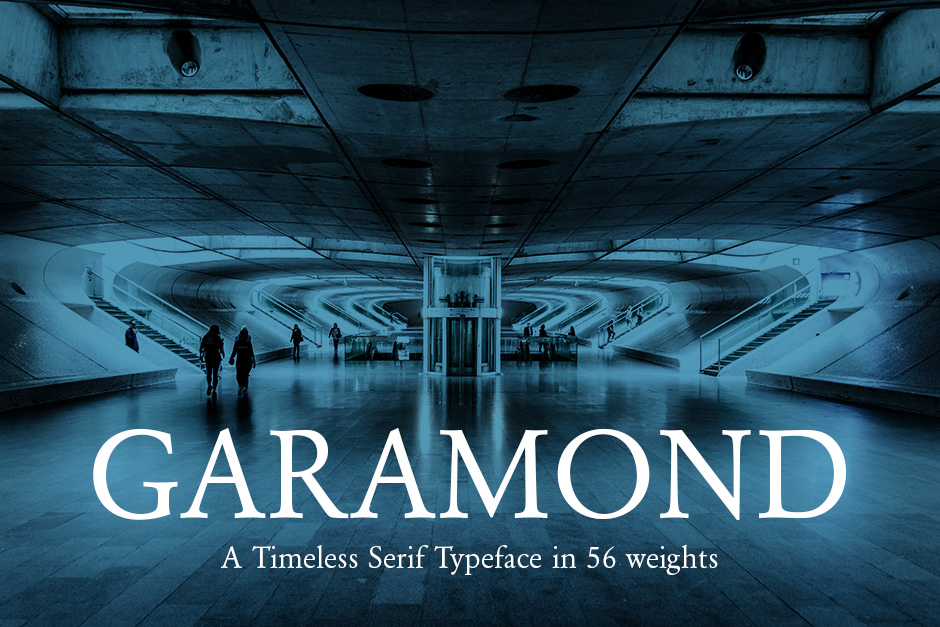
Helveticaと双璧をなすフォント「GARAMOND」
Beauty Style Font Duo
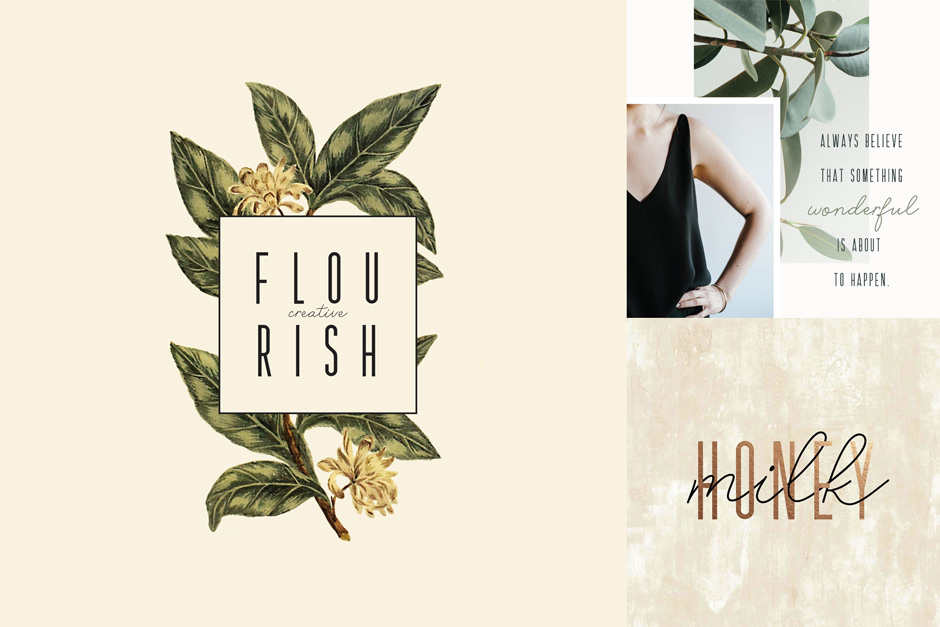
女性向けのデザインに合いそうな「Beauty Style Font Duo」
Portabella
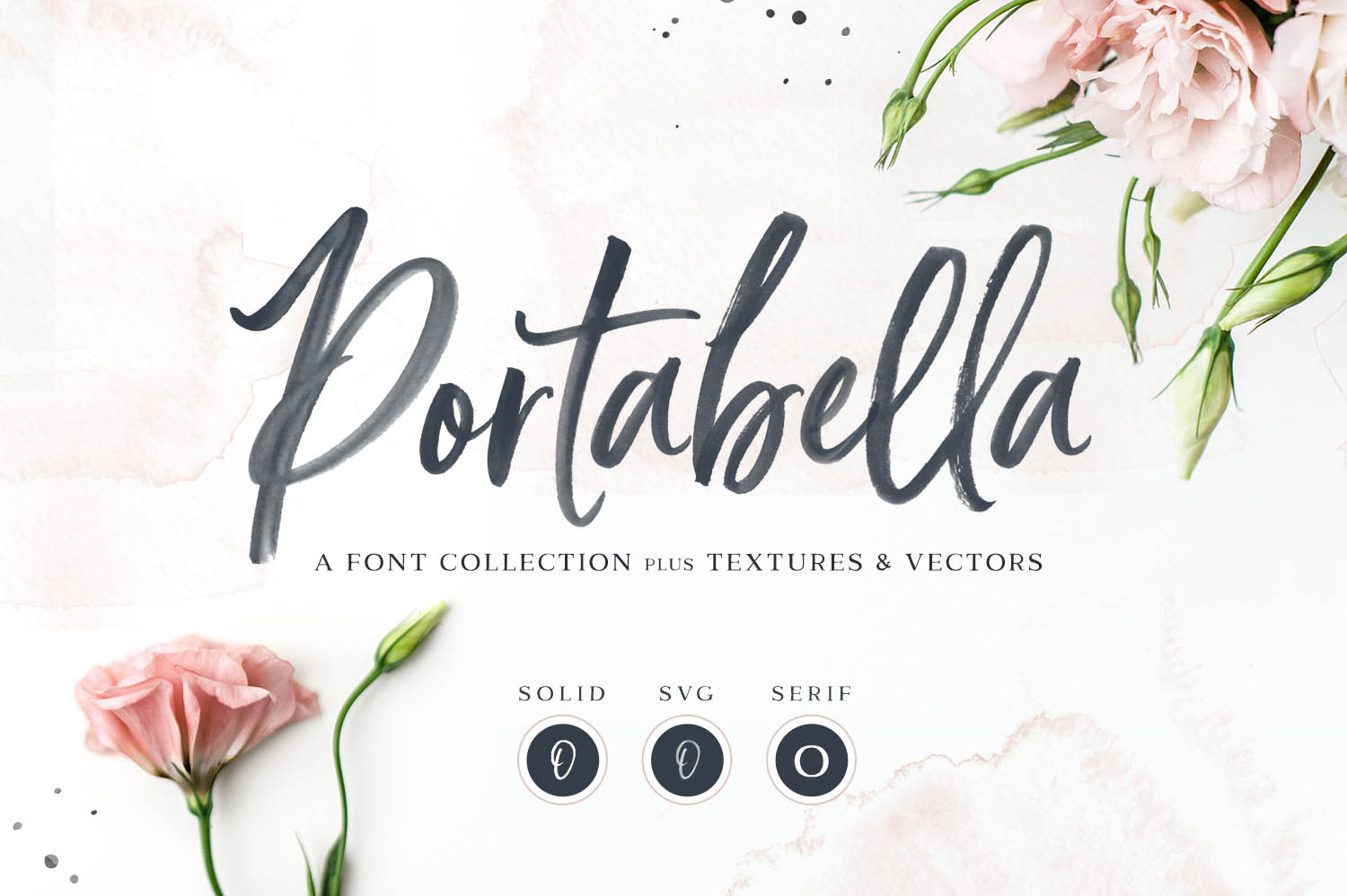
高品質な手書き風フォント「Portabella」
Starlit Drive Signature Font
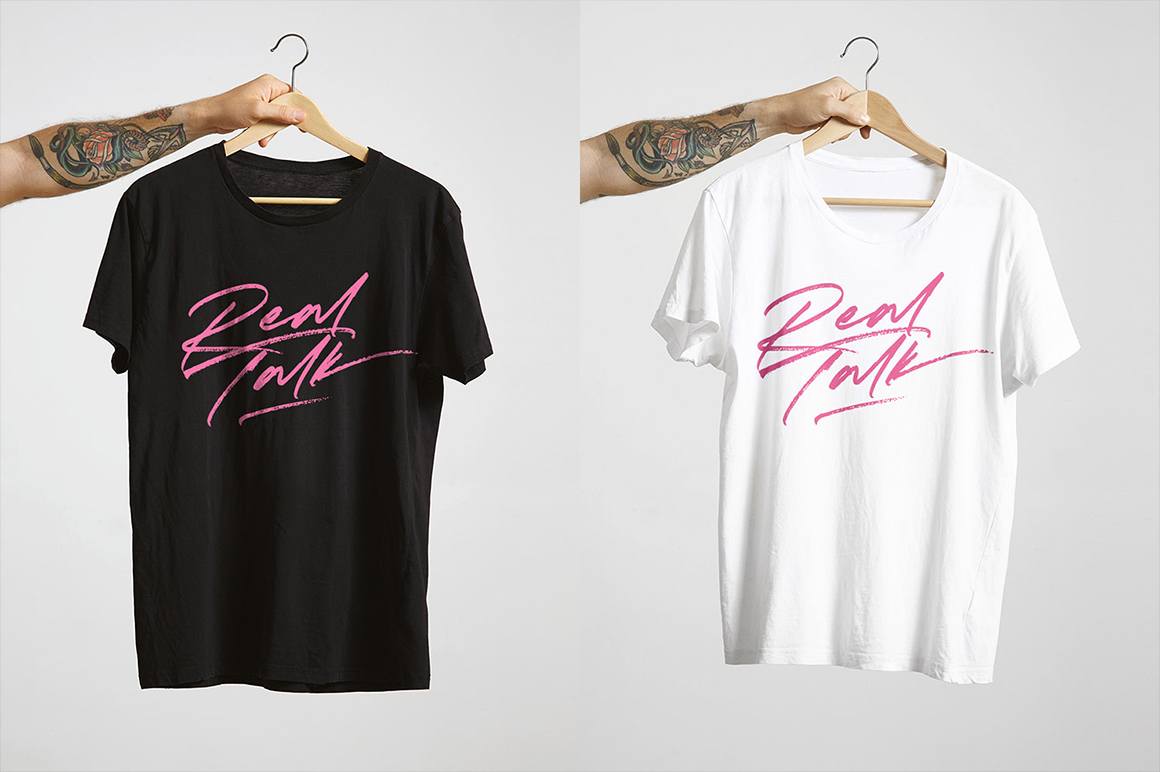
ストリート系やTシャツにぴったりの「Starlit Drive Signature Font」